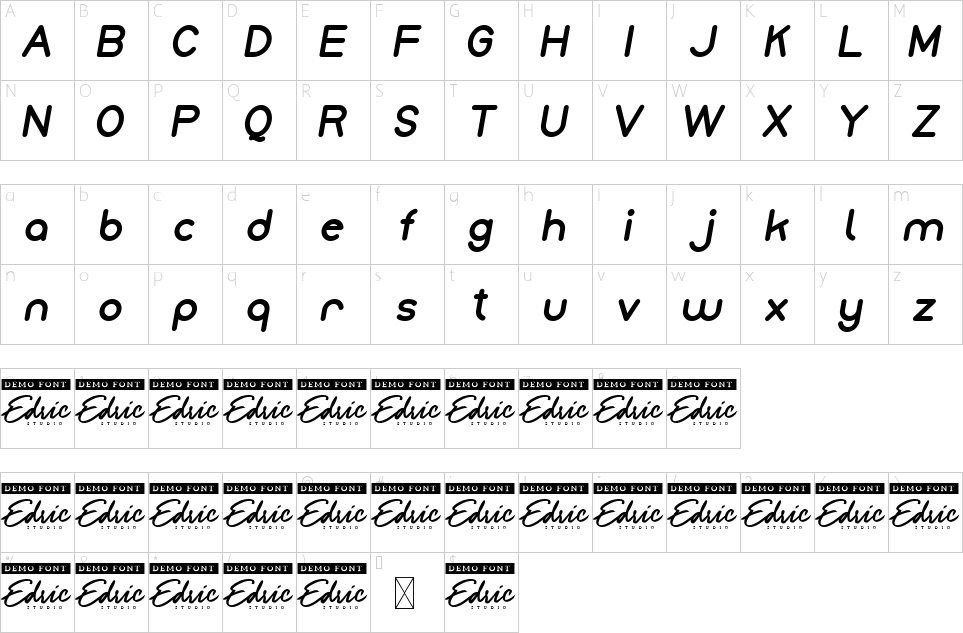
A Monice font é um belo e versátil recurso para designers gráficos, disponíveis tanto para sistemas Windows quanto para Mac. Desenvolvida pelo estúdio EdricStudio, esta fonte grata está entre as muitas opções que o site 1001 Free Fonts oferece. Com 5. 066 downloads realizados, a Monice já se tornou um favorito de muitos designers ao redor do mundo, procurando por fontes de alta qualidade que possam ser usadas livremente em seus projetos. Com sua elegância e facilidade de uso, a Monice pode se tornar uma opção irresistível para qualquer projeto de design que você esteja planejando.